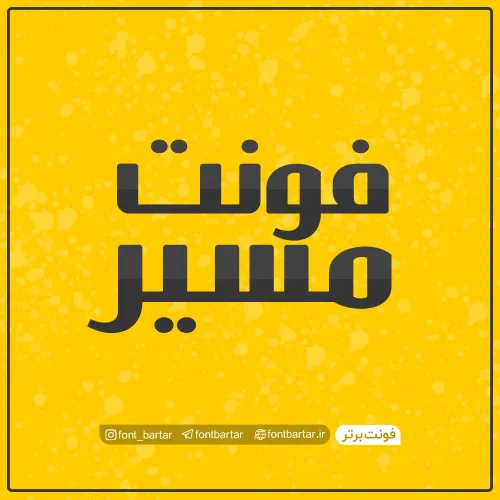
فونت فارسی مسیر
فونت مسیر مورد استفاده برای:
• طراحان وب سایت و گرافیست های خلاق می توانند از این مجموعه زیبا فونت در طراحی پروژه های تبلیغاتی و تجاری خود کمک بگیرند.